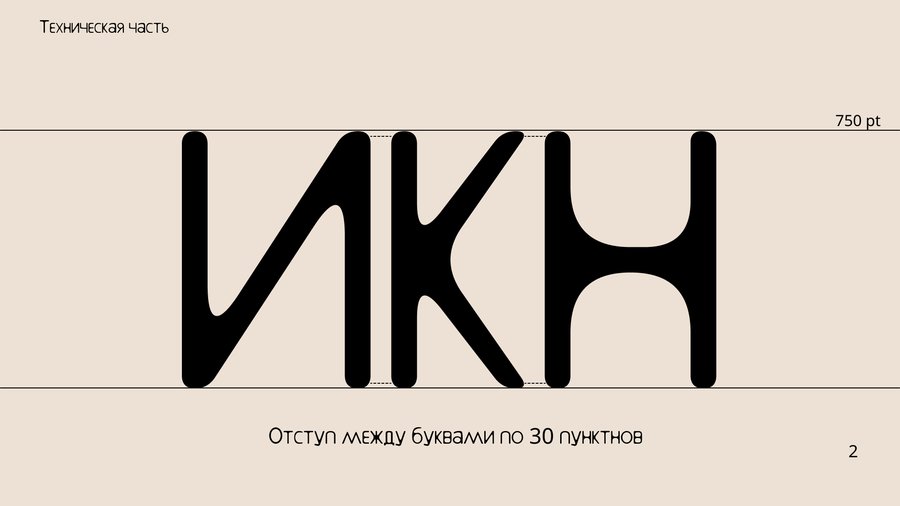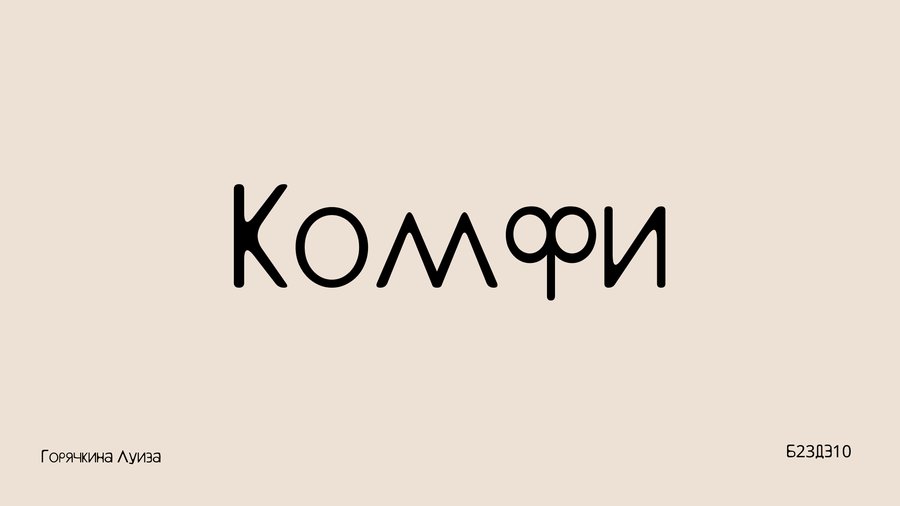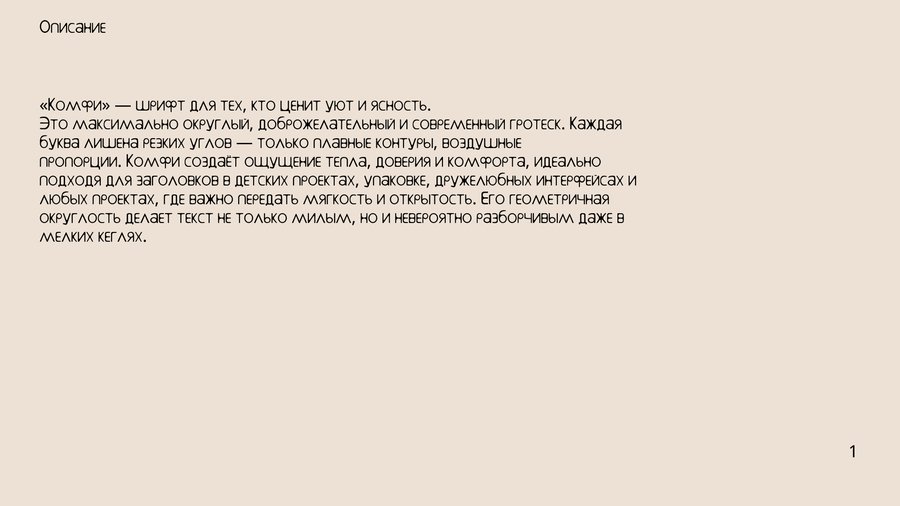
Я представляю вам шрифт «Комфи» — уютный и мягкий шрифт, который максимально округлый без каких-либо резких углов. Отлично подходит как для заголовков, так и для наборного текста.